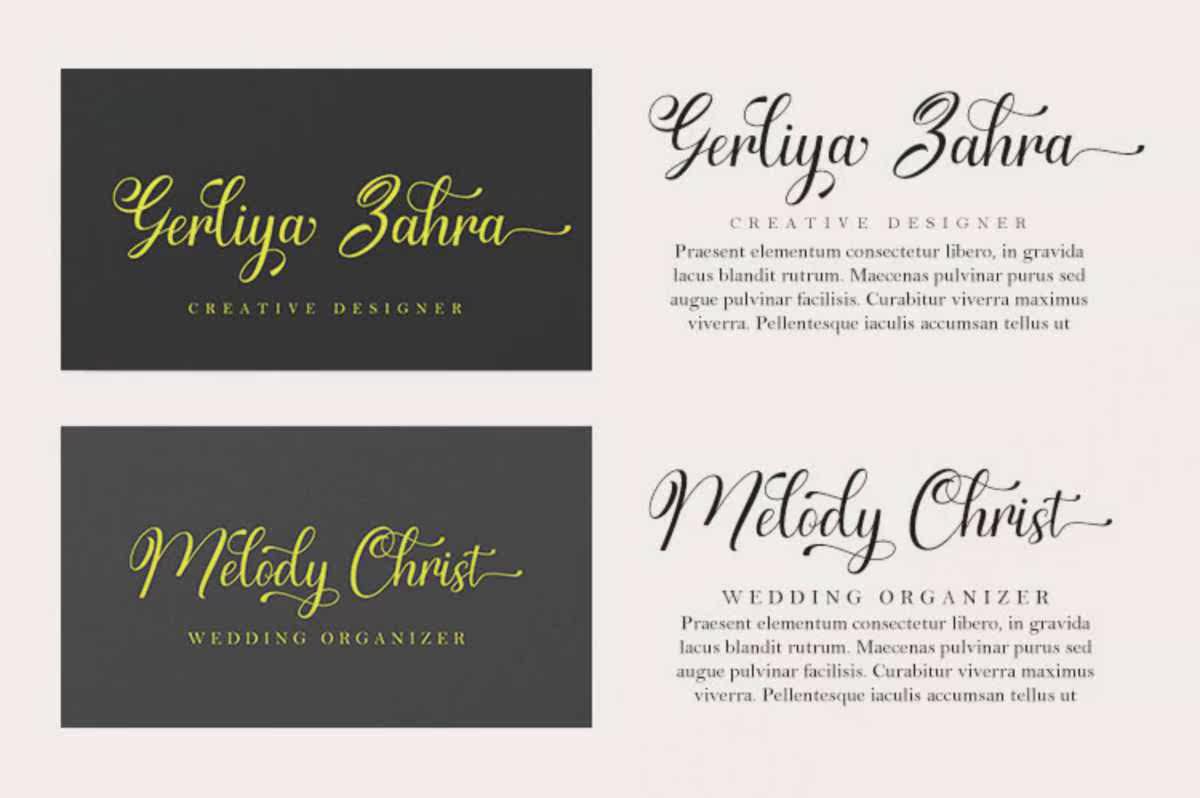
Gerliya书法字体是一种具有临时氛围和特殊字体的美丽脚本字体,灵感来自于一种非经典的书法。这种字体不厚、平衡、多样,其设计旨在增强项目的美感。Gerliya书法字体是一种具有临时氛围和特殊字体的美丽脚本字体,灵感来源于一种无齿的古典书法。这种字体的设计不需要太厚、平衡和多样,而是为了增强您的项目的美感。